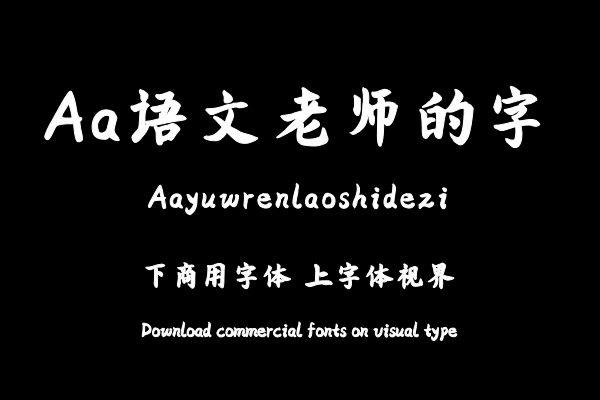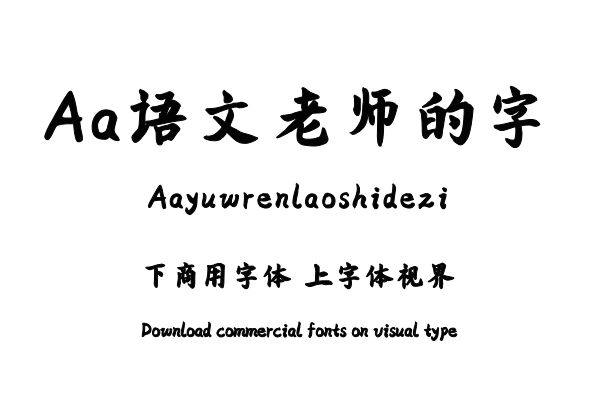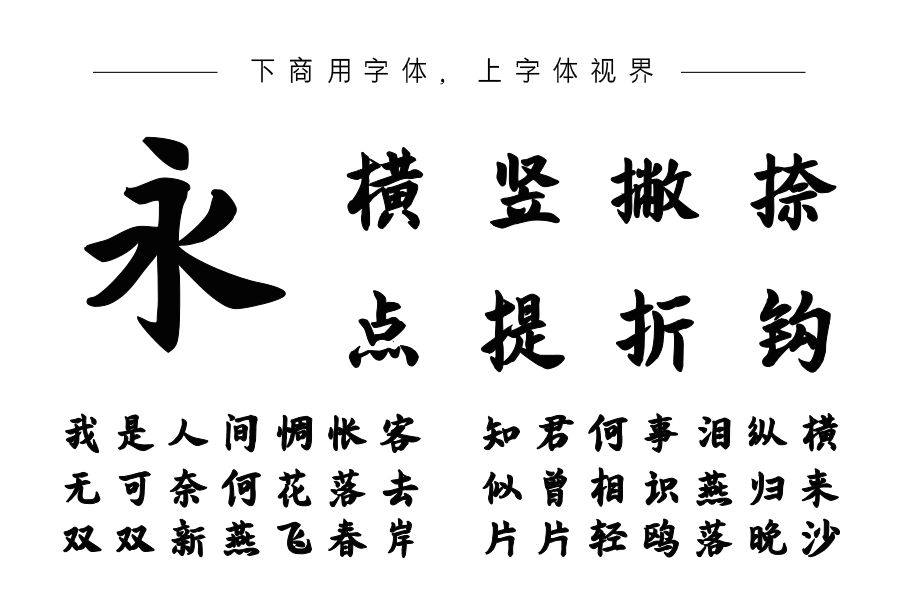
Aa语文老师的字是一款软笔字形字体,其结构以传统楷书的体势为基础 ,笔法灵活,笔画饱满,字形端正,整体风格稳重大方。多作为标题字体使用,适用于古风、人文等主题。购买须知:“下载服务费”与“字体VIP”所获得字体 仅用于个人非商用, 商用请联系付费授权。本字体为电脑用字,手机没有root权限不支持直接手机换字(手机如何root,请自行百度搜索教程)。购买前请先 了解清楚后再付款 ,字体为虚拟产品无法回收 一旦购买不支持退款。